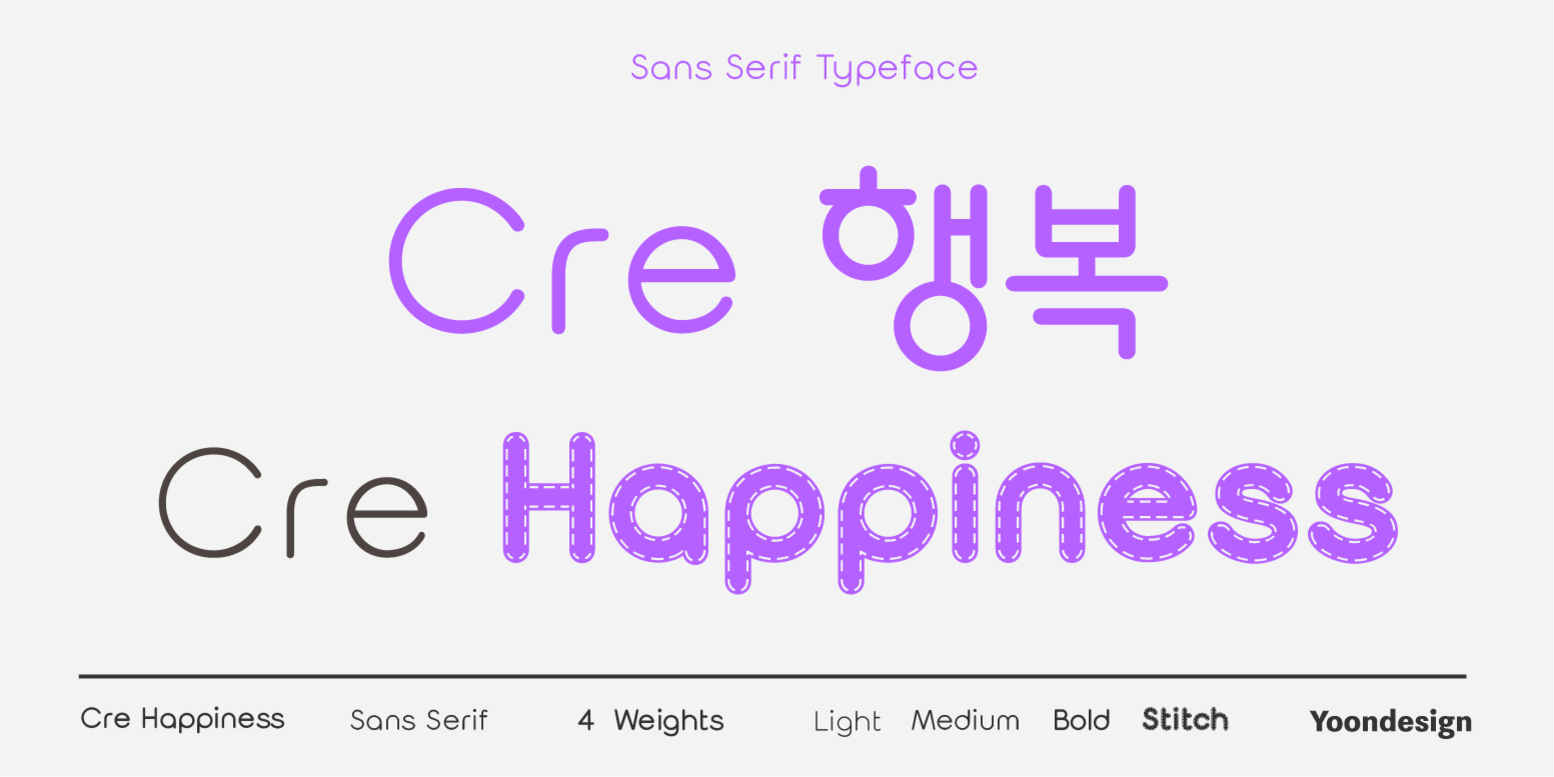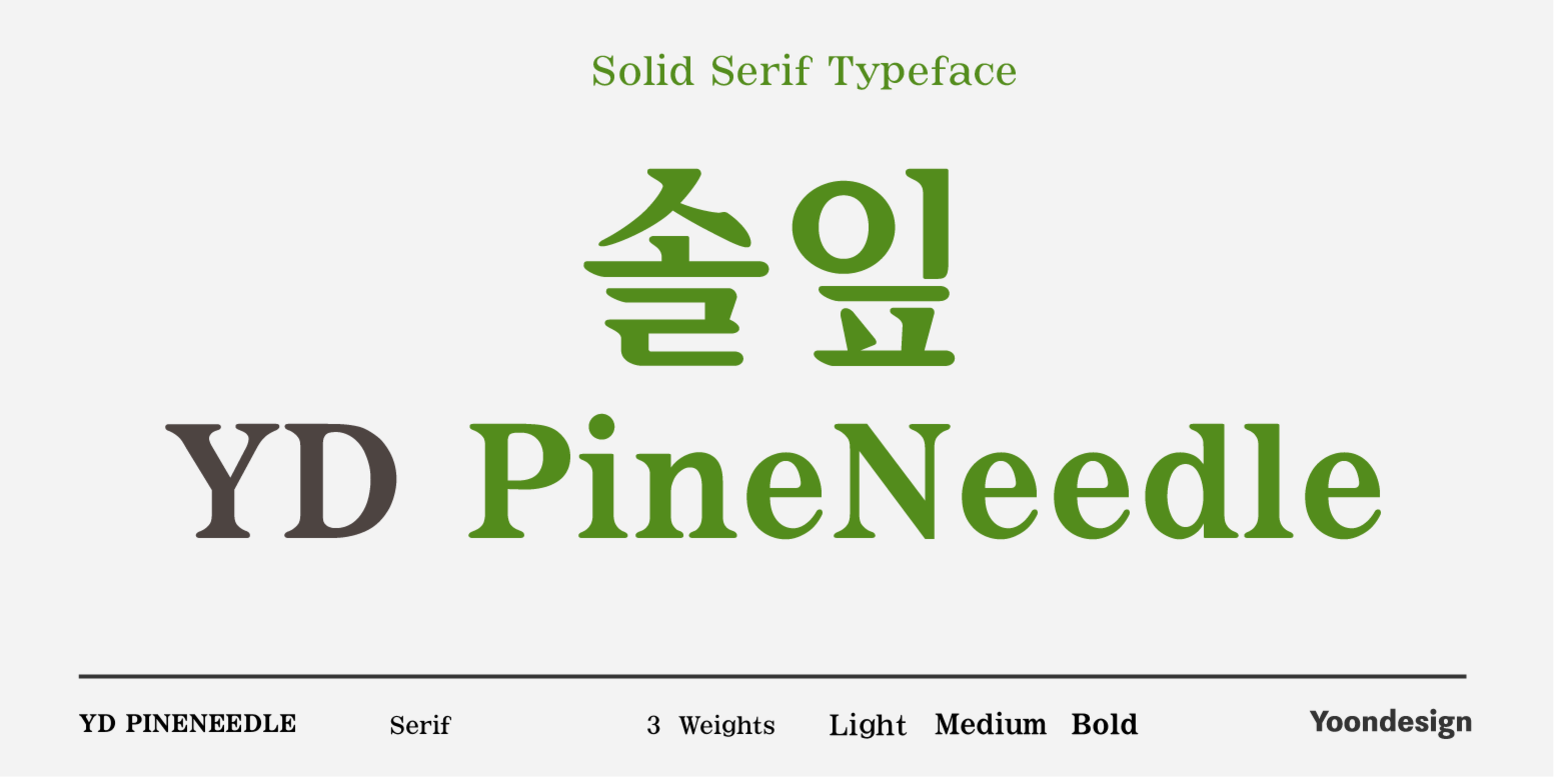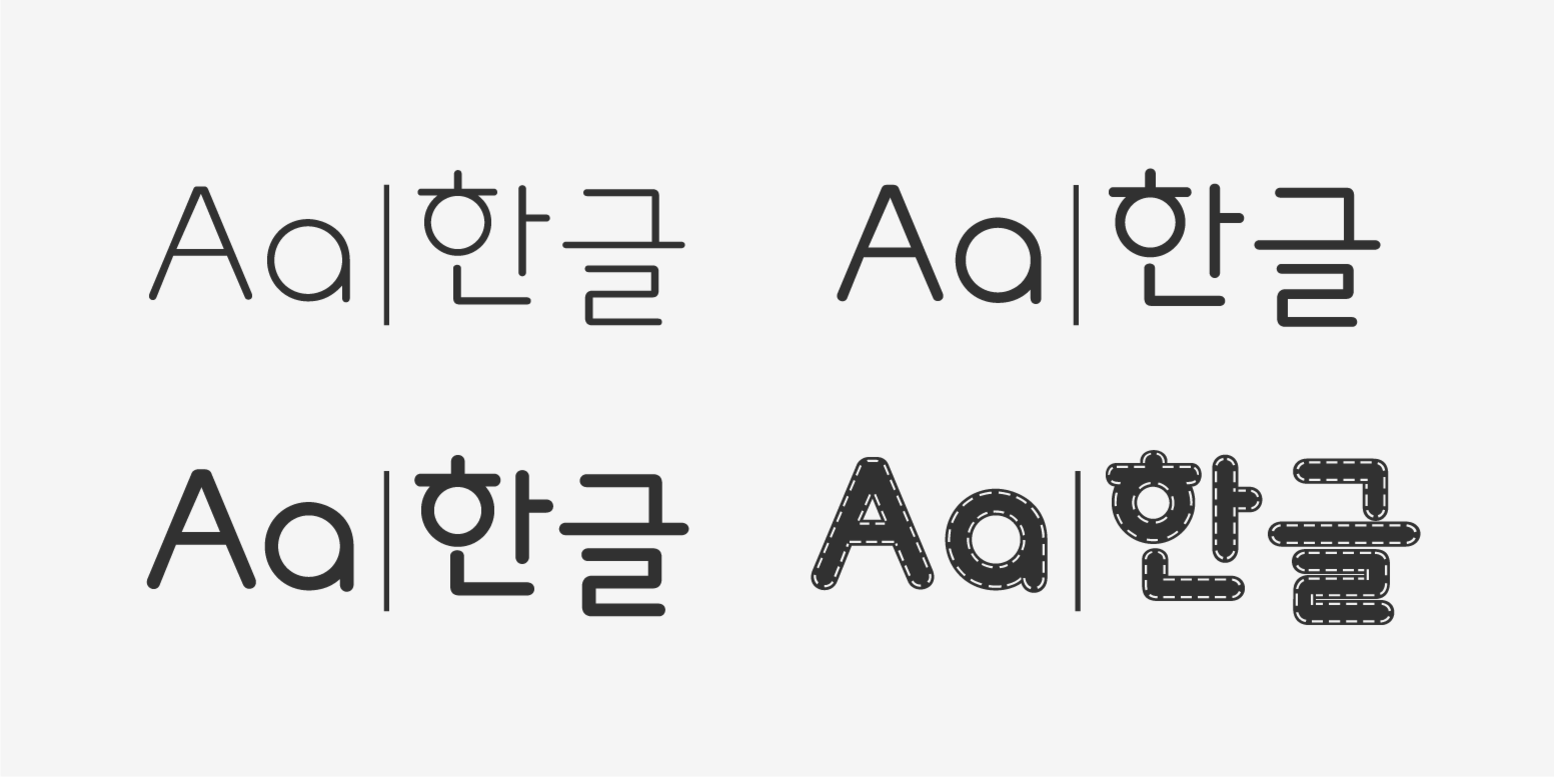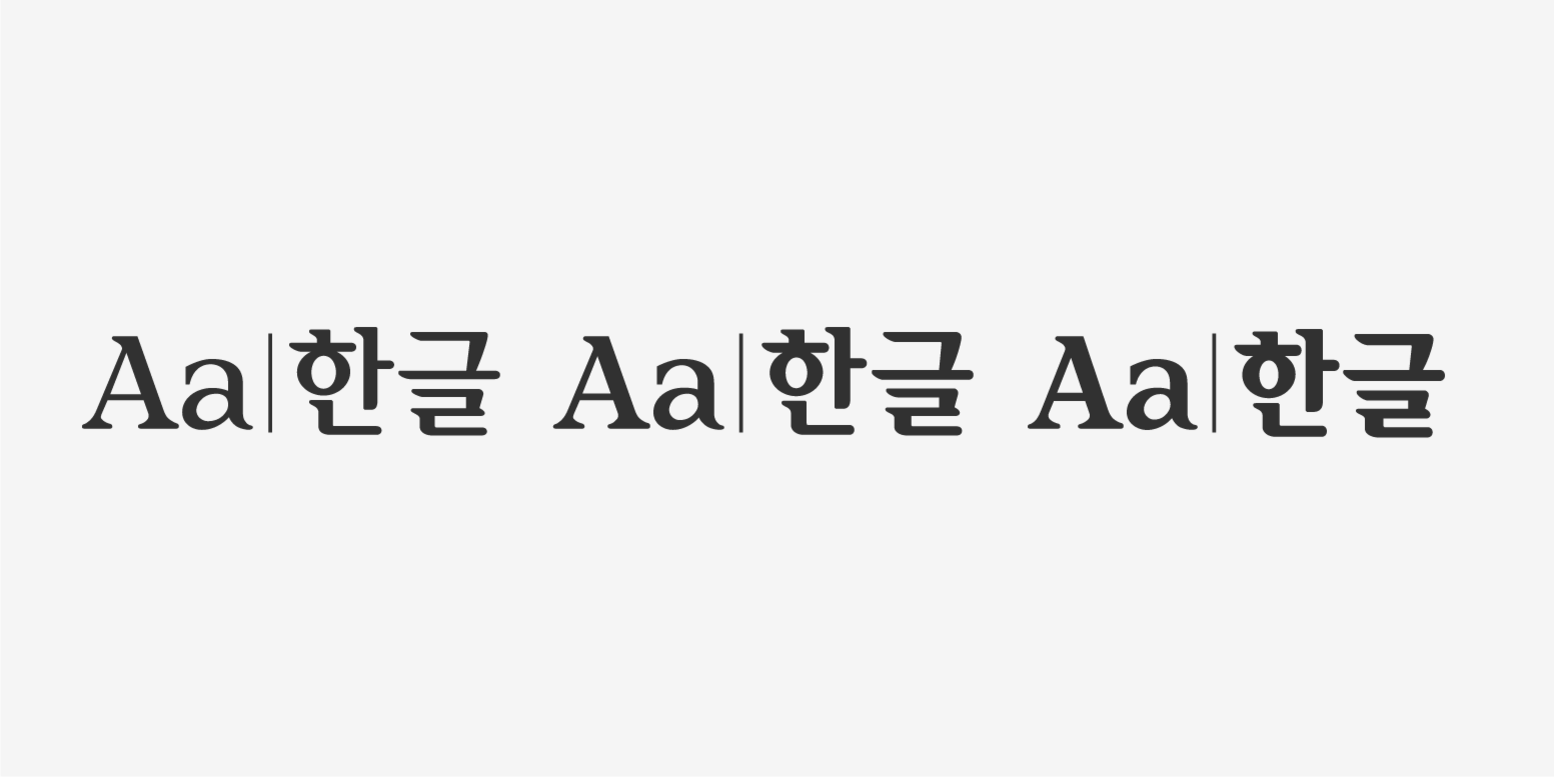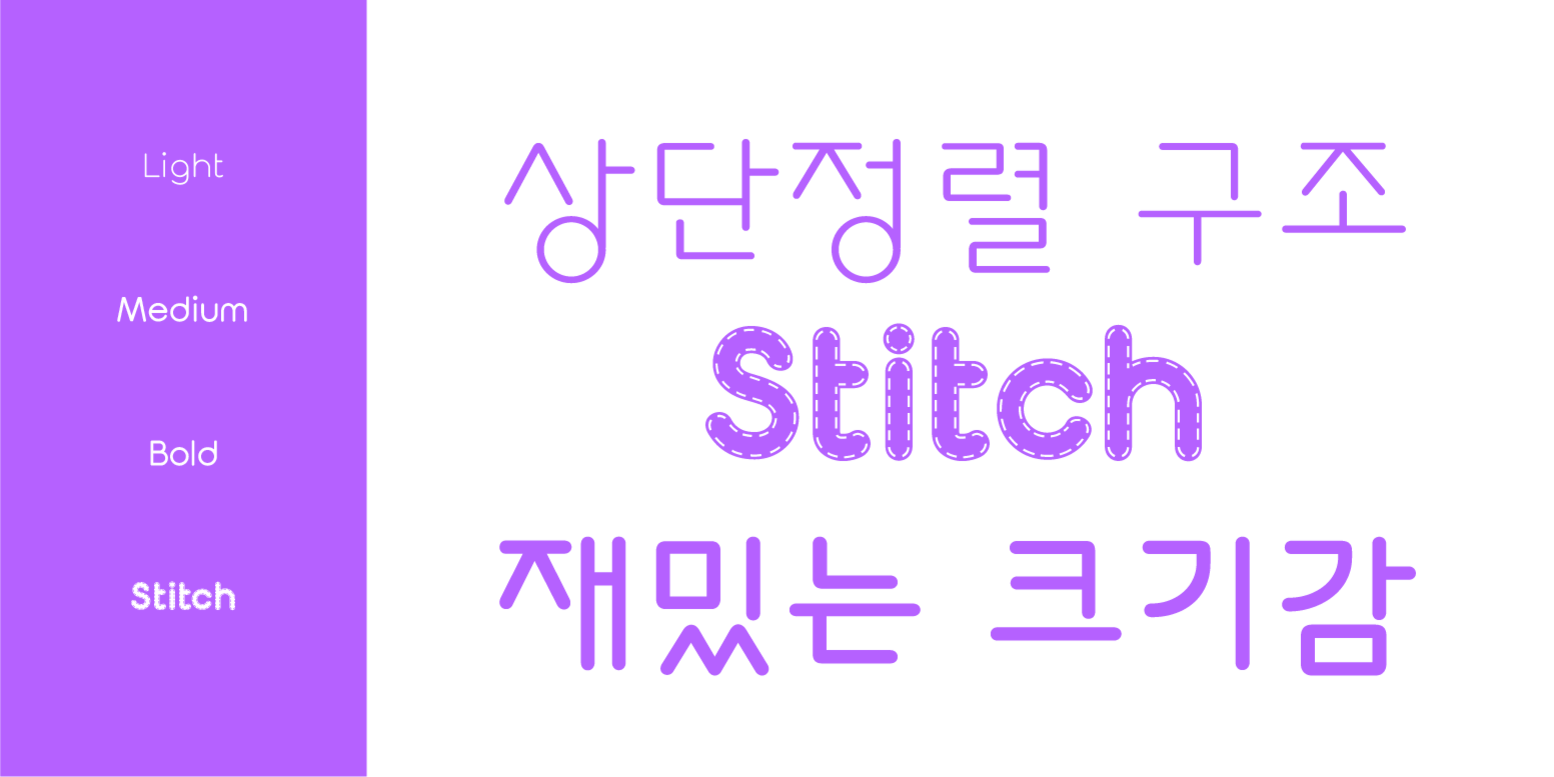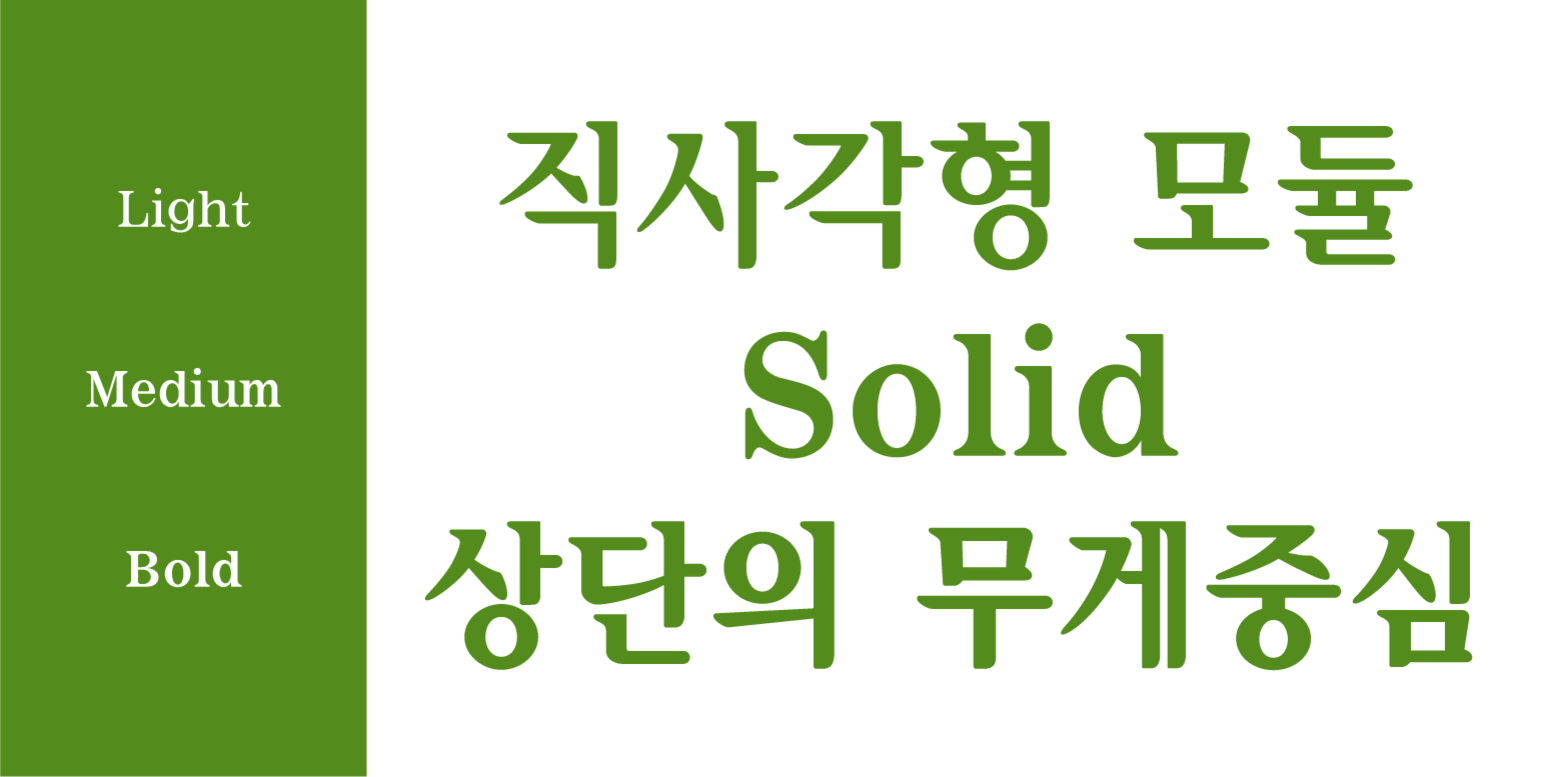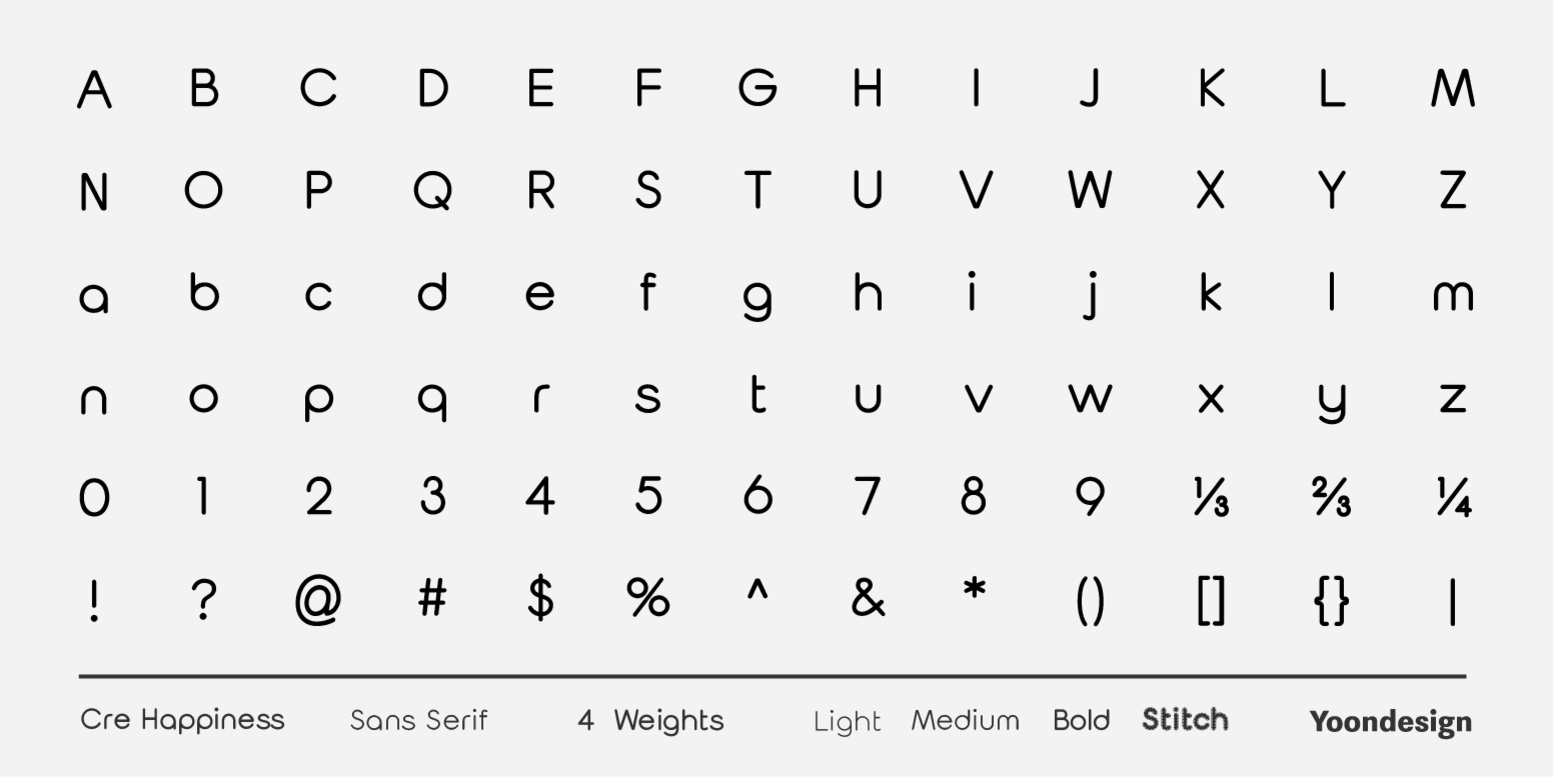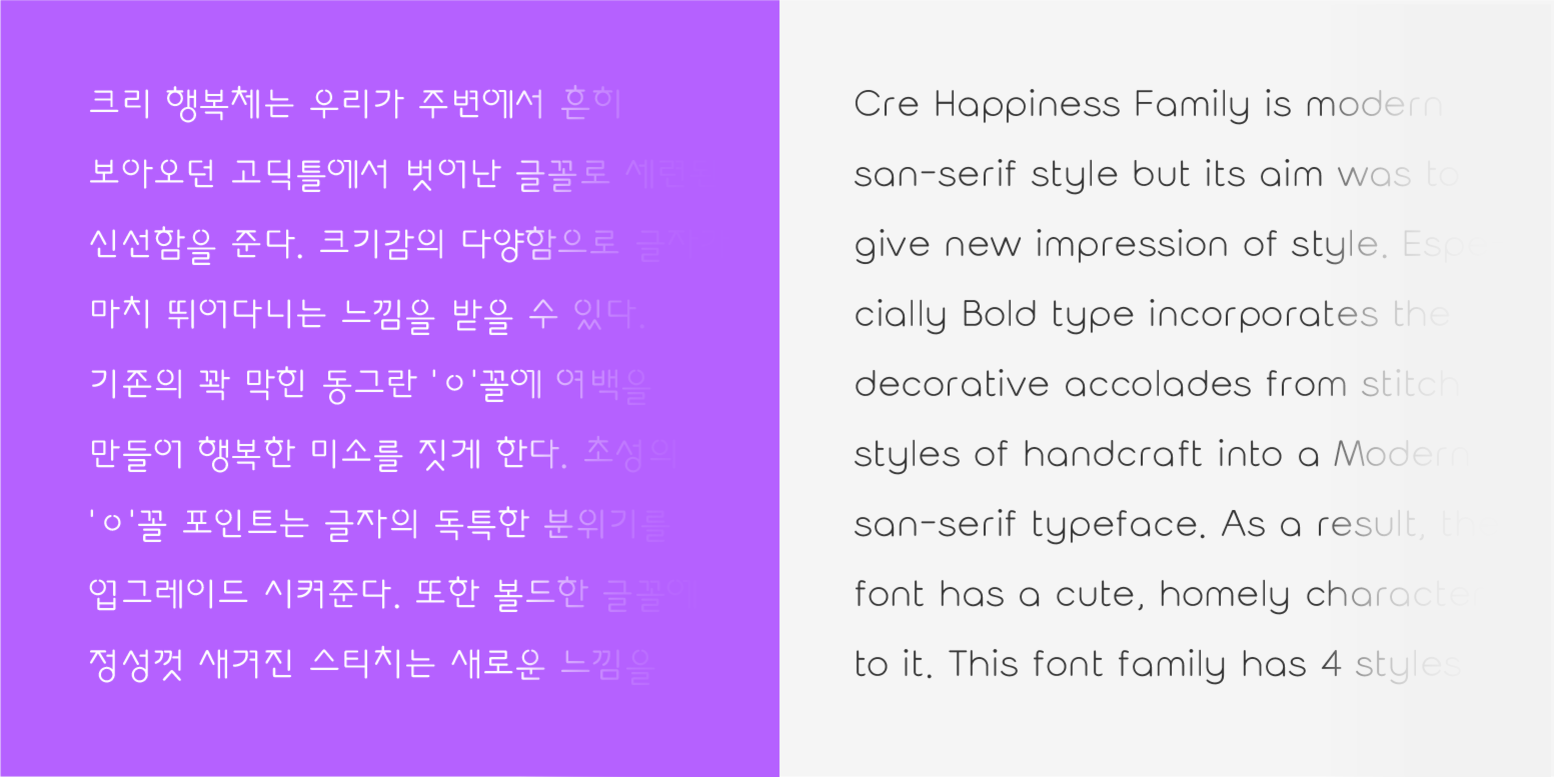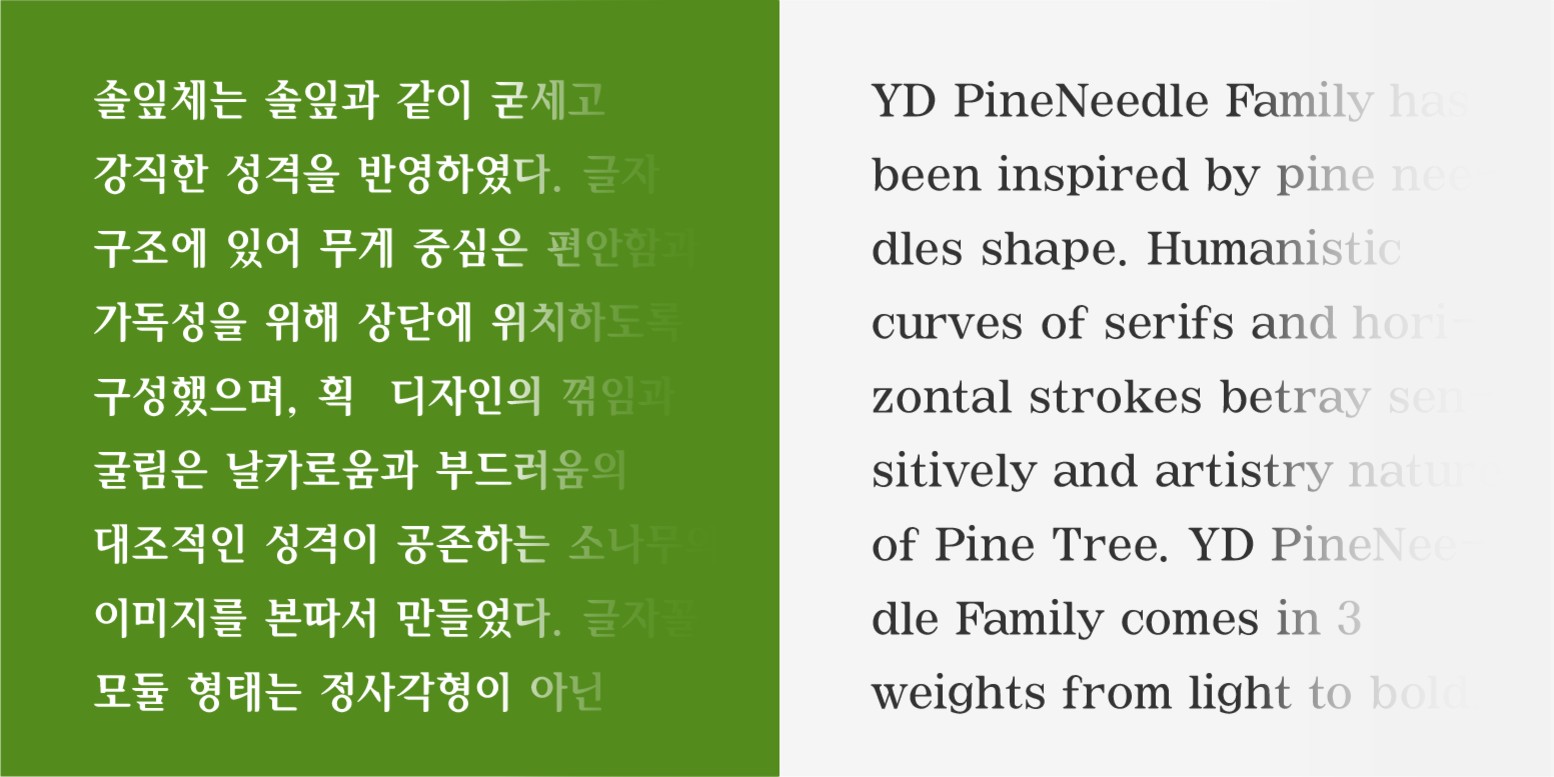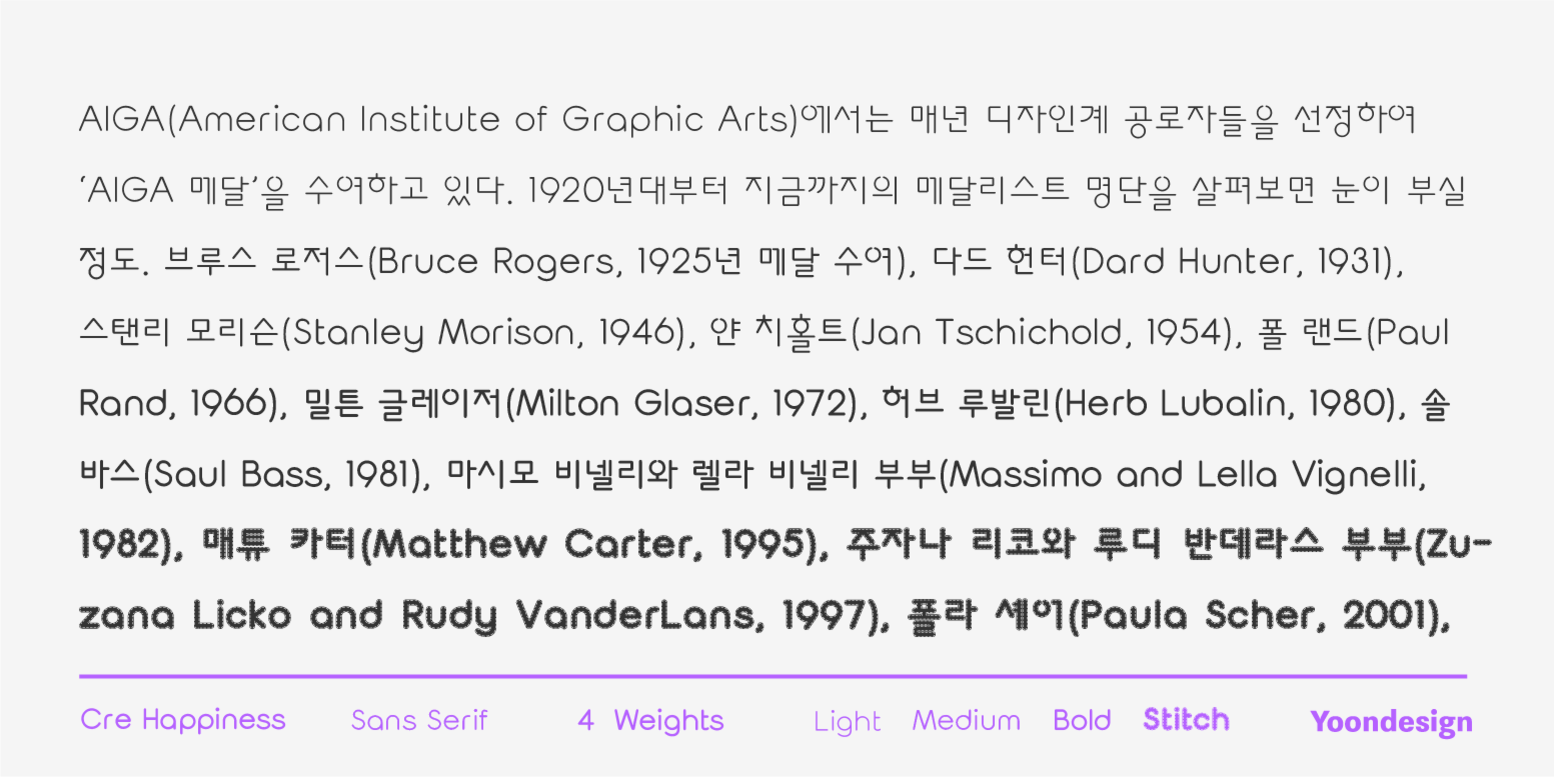
伴随全球化浪潮,越来越多的企业开始将业务拓展至韩国市场。无论是游戏、影视、电子商务,还是其他行业,韩国市场凭借其成熟的数字生态、高度发达的文化产业和强劲的消费力,成为出海的重要目的地。
打造符合当地审美、精准传递品牌信息的视觉设计,对企业在当地构建起良性的消费者沟通至关重要,而韩文字体的选择正是其中不可忽视的一环。
韩文字体主要有两大风格类型:
- 명조체(明朝体),类似于中文的宋体/楷体,相当于西文字体中的衬线体。
- 고딕체(Gothic 体),类似于中文的黑体,相当于西文字体中的无衬线体。
除这两种主要风格外,还有适于特定场景使用的各类手写体与装饰体等。
蒙纳携手 Yoondesign、StudioJASO、HeummDesign、S-Core 等知名韩国字体设计公司,不断拓展韩文字库,为品牌提供更多元的创意选择。因此,本文精心挑选了 18 款风格各异的韩文字体,助力品牌在韩国市场建立独特形象,实现更有效的本地化沟通。
# Gothic 体 고딕체
Seol Sans / Carmen Sans / RyuGothic / HU Sansans KR / HU Flatwhite KR / YD Gothic 200 / Cre Happiness
1|Seol Sans
人文主义 / 柔和自然
Foundry:Monotype
Seol Sans 为韩文字母设计提供了一套全新的解决方案,从而能与拉丁字母和谐混排。作为蒙纳首款原创韩文字体,Seol Sans 以人文主义视角重塑了传统韩文字符刚硬的造型特征,其设计更贴近手写字体的自然曲线。
该字体可与蒙纳旗下西文字体 Neue Frutiger World、日文字体 Tazugane Gothic 和中文字体翔鹤黑实现完美搭配。对于希望保持视觉识别统一性,并在韩国市场传递一致品牌声量的全球无衬线字体使用者而言,Seol Sans 是理想选择。
2|Carmen Sans
几何风格 / 简约清晰
Foundry:studioJASO
Carmen Sans 是一款几何无衬线字体,以简约清晰的笔形传递现代活力。其韩文字体通过柔和的曲率与结构设计,与拉丁字体保持一致的视觉基调,并通过调节字高比例,使其更适配展示设计需求。
该字体共含 9 款字重,能够无缝应用于从品牌形象塑造到整合应用的全媒介平面设计场景,满足多元化的创意表达。
3|RyuGothic
人文主义 / 柔和沉稳
Foundry:studioJASO
RyuGothic 字体是对韩文黑体风格进行的人文主义诠释,以柔和沉稳的视觉语调传递信息。其通过收窄韩文字符辅音字腔与拉丁小写字母字腔的设计,在两大字符集间建立起结构统一感。
既保证了长文阅读场景的流畅性,又具备全媒介适用性。标点符号位置特别遵循韩文排版习惯进行优化设计。
4|HU Sansans KR
现代流畅 / 富有活力
Foundry:HeummDesign
Sansans KR 是一款无衬线韩文字体,采用坚实且现代的矩形设计,展现出强劲而明亮的能量感。
通过在首字母的首个辅音下方留白,并延续曲线的流畅感,使字体整体呈现出年轻而富有活力的氛围。该字体提供四款字重,增强了其在不同场景下的适用性。
5|YD Gothic 200
简洁易读 / 实用干净
Foundry:Yoondesign
YD Gothic 200 是迄今为止韩国最常见的字体之一,在设计师偏好和客户偏好方面均名列前茅。作为一款简洁易读的现代无衬线字体,其简单的单线结构给人以实用、干净、简约的观感。
细节设计亦显惊艳,丝毫不会呆板平淡,有助于强调文字或标题,已在杂志和书籍封面等场景广泛使用。
6|Cre Happiness
标题字体 / 装饰元素
Foundry:Yoondesign
Cre Happiness 是一款现代无衬线字体,旨在带来全新的视觉风格。其中,Bold 字重特别融入了手工刺绣风格的装饰元素,使整体呈现出可爱温馨的氛围。
该字体包含 4 款字重,尤其适用于大尺寸展示和标题设计。
7|HU Flatwhite KR
复古氛围 / 流畅曲线
Foundry:HeummDesign
这是一款灵感源于馥芮白,专为标题设计的复古风格字体。元音的首个笔画采用内凹设计,搭配点状元素,进一步增强了层次感。字体的特色在于辅音中的点状细节,以及“ㄱ”、“ㅅ”、“ㅈ”末端的纤细收笔,勾勒出流畅的曲线美感。
虽然整体框架稳定,但通过笔画的强烈对比营造出宽敞的内部空间,使字体呈现出清爽的视觉效果。
# 明朝体 명조체
Blatt / Schola Serif / Sejam / HU Cheonggye KR / YD Myungjo 200 / YD PineNeedle
8|Blatt
高对比度 / 复古简洁
Foundry:studioJASO
Blatt 是一款兼具复古与现代风格的字体,融合了毛笔的柔和笔触。其竖直与横向的高对比度笔画以及较宽敞的字形结构,塑造出了简洁明了的风格;同时笔画的收尾则借鉴了西文衬线体的细节。
作为一款标题字体,Blatt 在大尺寸下能展现每个字母的细节,呈现理想的视觉效果,同时在小尺寸下依然保持良好的可读性。
9|Schola Serif
古典风格 / 锐利精致
Foundry:studioJASO
Schola Serif 是一款新古典风格的衬线体,以现代且独特的方式重新诠释字体的结构与表现力。其字形线条利落,视觉清晰,具备锐利的衬线与精致细节。在标题、副标题或 16pt 以上字号使用时,能展现独特的个性。
该字体提供 5 款不同字重,支持 60 多种语言,并包含 9 种 OpenType 特性。无论是平面设计还是品牌标识,Schola Serif 都能完美适配。
10|Sejam
纤细优雅 / 现代美学
Foundry:studioJASO
Sejam 本意指传统的装饰性发簪,也是这款字体的灵感来源,其设计特点包括极纤细的横笔画,以及优雅且富有装饰感的衬线。
简洁利落的字形符合现代美学,而高对比度与传统对称结构则赋予其精致的气质。这款字体还支持连字等多种 OpenType 特性,适用于奢侈品、海报、包装等多种应用场景。
11|HU Cheonggye KR
宽阔有力 / 复古衬线
Foundry:HeummDesign
HU Cheonggye KR 是一款用于标题设计的字体,笔画粗壮,横笔宽阔,整体呈现复古风格。为了凸显复古字体的特点,设计上采用了横竖笔画粗细对比,并加入了直角衬线。
12|YD Myungjo 200
简洁易读 / 舒适柔和
Foundry:Yoondesign
YD Myungjo200 是一款在韩国备受青睐的衬线字体,字符高挺简洁。这款字体结合了美学与功能,使文本具有极高的可读性。
这款优雅的人文主义风格字体非常适于精美排版,无论是用于书籍正文还是标题内容,都有着舒适柔和的观感。
13|YD PineNeedle
人文曲线 / 简洁舒适
Foundry:Yoondesign
YD PineNeedle 字体灵感来自松针的形状。衬线的人性化曲线和横向笔触体现了松树的敏感性和艺术性。YD PineNeedle 系列涵盖 3 款字重,可用于海报和各种平面设计场景。
# 装饰及手写体
HU Hikiki KR / HU Mois KR / YD Gogooryo / Cre ChocoCookie / DS RomanticGuy
14|HU Hikiki KR
生动活泼 / 童趣可爱
Foundry:HeummDesign
HU Hikiki KR 是一款手写字体,灵感源于孩子渴望快些长大并模仿成年人的心情,在设计上有着极强的节奏感和韵律感,能够为各种创意项目增添生动和趣味,特别适合用于儿童相关的品牌、广告以及年轻化的视觉传达设计中。
15|HU Mois KR
轻盈流畅 / 自然倾斜
Foundry:HeummDesign
HU Mois KR 是一款具有速度感的书法字体,笔画轻盈流畅,字形自然倾斜,仿佛每个字都带着书写时的情感与节奏。
这款字体适用于需要表现自由活力的设计项目,如品牌标识、广告、海报等,能够有效传递一种现代而富有表现力的视觉风格。
16|YD Gogooryo
自然触感 / 简洁生动
Foundry:Yoondesign
YD Gogooryo 采用了如炭笔书写而出的触感,给人一种自然拙朴的感觉。字体线条富有手工味道,又不失现代的简洁和生动,非常适于书籍封面、艺术展览、平面海报等轻巧灵动的视觉传达设计项目。
17|Cre ChocoCookie
俏皮可爱 / 甜美轻松
Foundry:Yoondesign
Cre ChocoCookie 字体家族具有俏皮可爱的风格,字符仿佛巧克力曲奇饼干的形状。其甜美的氛围和可爱的外观使其成为任何需要传递幸福、轻松氛围的创意设计的理想选择。
18|DS RomanticGuy
轻盈流畅 / 自然倾斜
Foundry:Yoondesign
DS RomanticGuy 字体既随性流畅,又如奶油般柔滑。它具有流畅的草书感字形,字母的描绘如同一张情歌专辑般细腻。
这款字体涵盖 3 款字重,适用于婚礼请柬、公告、礼品及精美包装、杂志排版等项目,以其独特的浪漫气息为设计增添一份精致与温暖。
"title": "为什么韩国的设计独特?原因可能是这些美妙的字体……"